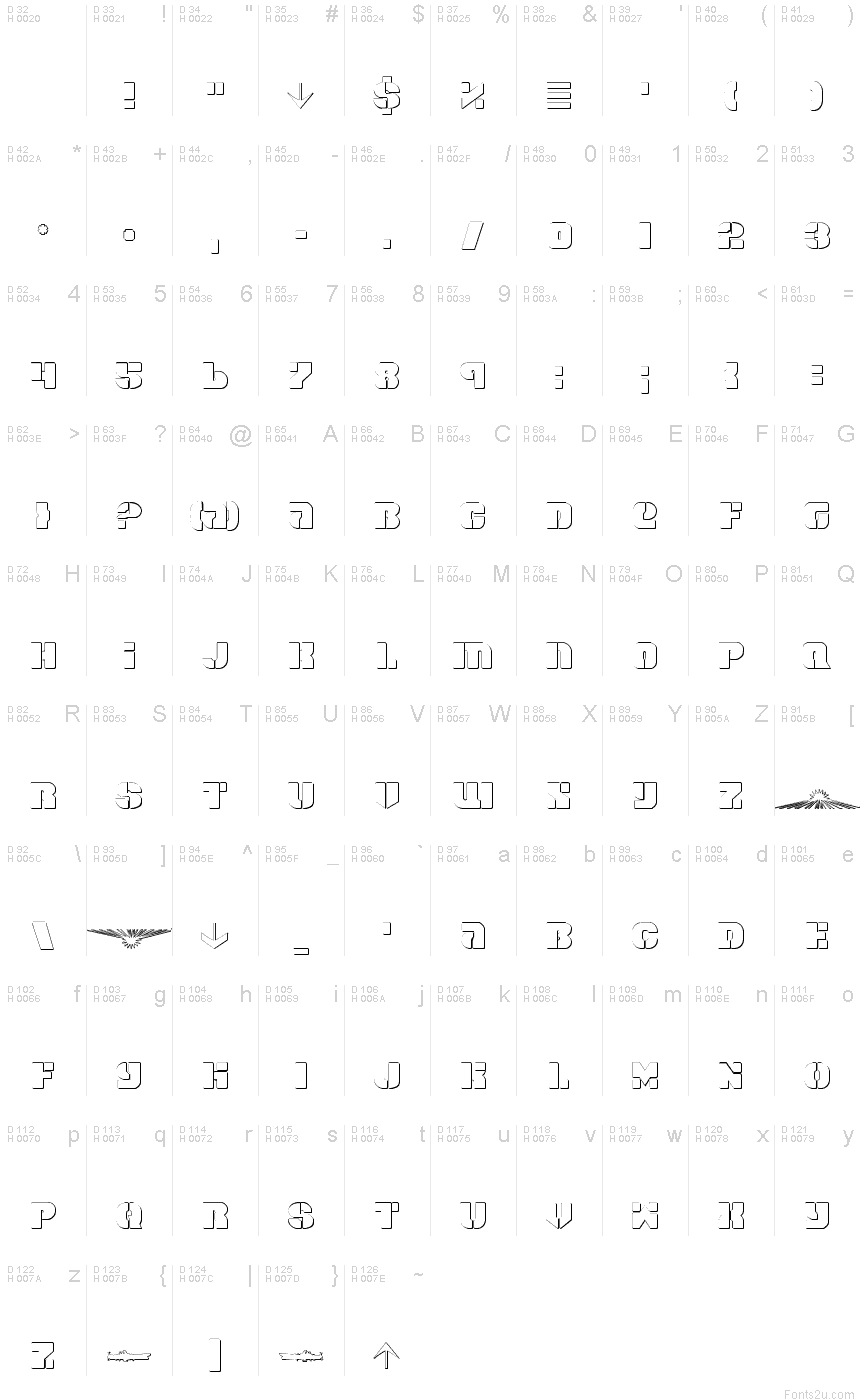
Space Cruiser Shadow od Iconian Fonts to darmowy, utrzymany w stylistyce retro sci-fi krój pisma z dużymi, zaokrąglonymi literami i wbudowanym cieniem, który przywodzi na myśl okładki książek science fiction sprzed lat. Formy są szerokie, gładkie i wyraziste, a stopniowany wewnętrzny cień nadaje krojowi wygląd formowanego plastiku lub panelu sterowania, który powtarza się w każdym znaku.
Świetnie sprawdzi się na plakatach, logo w stylu arcade, okładkach albumów, opakowaniach i planszach tytułowych – wszędzie tam, gdzie darmowy font z tak dużą dawką futurystycznego vintage potrafi zbudować cały klimat projektu. Ponieważ cień jest częścią projektu, litery wyjątkowo dobrze sprawdzają się w krótkich nagłówkach i monogramach, gdzie ten warstwowy efekt statku kosmicznego z lat 70. pozostaje odważny i czytelny.
Space Cruiser Shadow